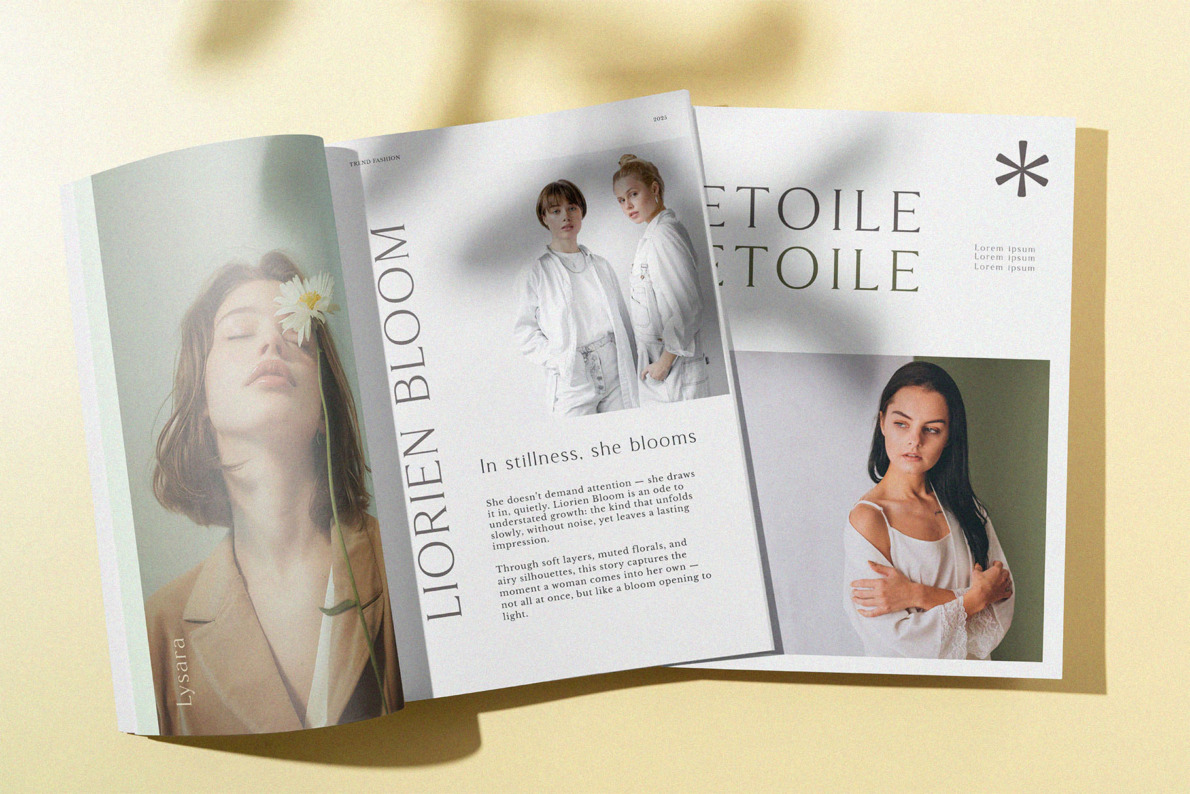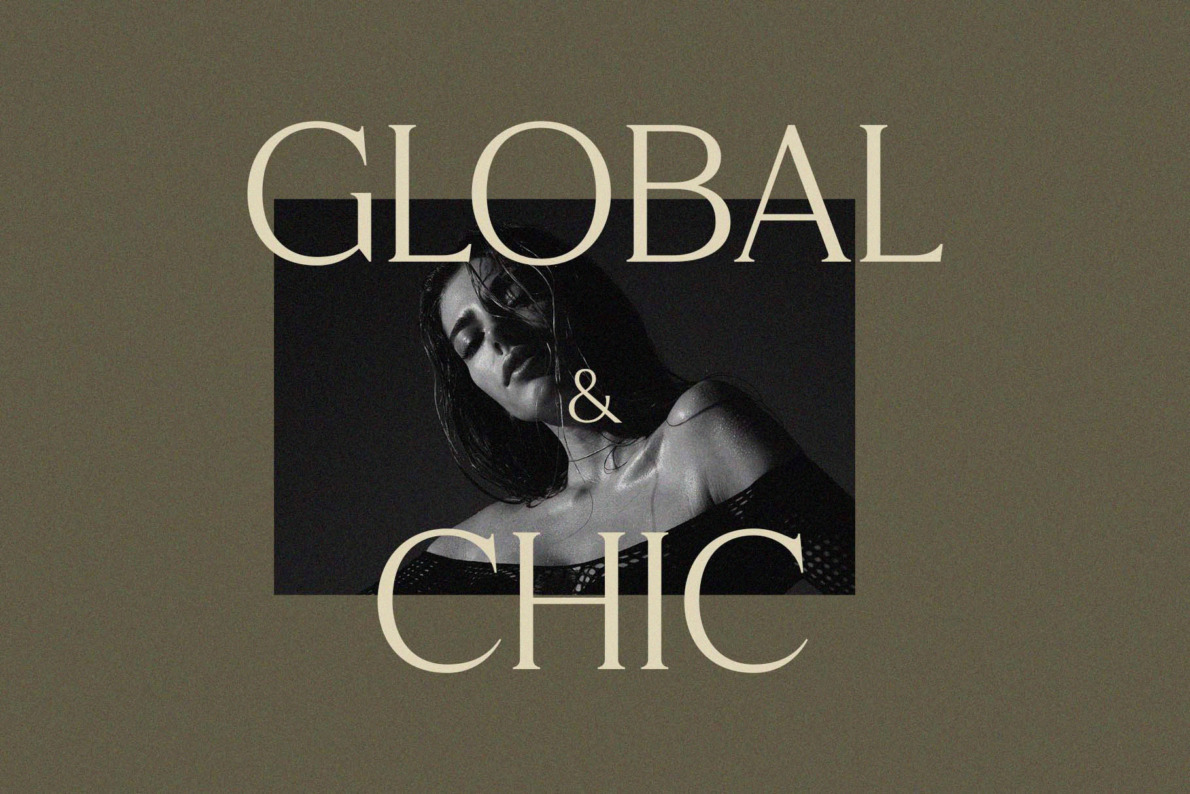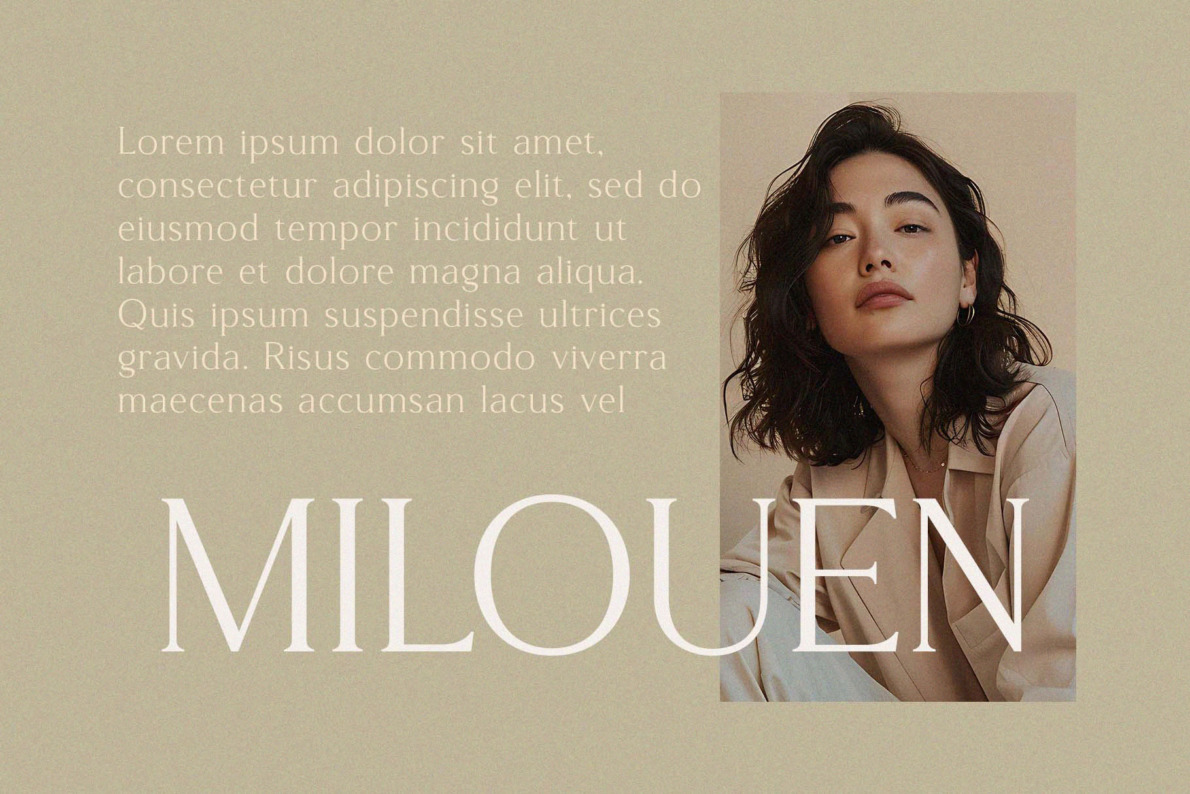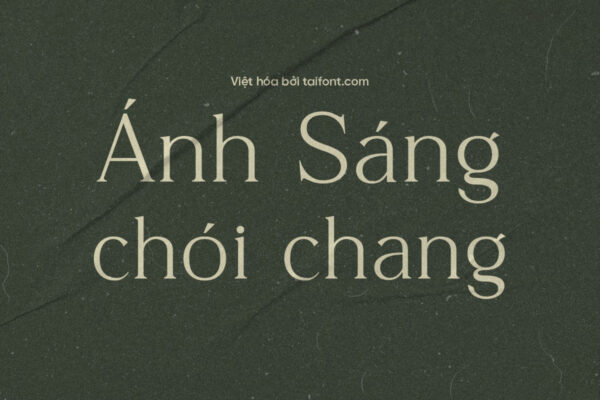
Giới thiệu về Font TF Galbety Việt hóa
TF Galbety Việt hóa là một font chữ có chân (serif) mang vẻ đẹp tinh tế, hiện đại và đầy cuốn hút. Với những đường nét được thiết kế tỉ mỉ, sắc sảo nhưng vẫn giữ được sự mềm mại, Galbety toát lên phong thái sang trọng và đẳng cấp, rất phù hợp cho những thiết kế cao cấp và đầy tính nghệ thuật.
Font này là lựa chọn lý tưởng để tạo nên sự ấn tượng và chuyên nghiệp, đặc biệt là trong các lĩnh vực yêu cầu tính thẩm mỹ cao:
- Thiết kế thời trang: Hoàn hảo cho các thương hiệu thời trang cao cấp, từ nhãn mác sản phẩm, lookbook, đến các chiến dịch quảng bá bộ sưu tập. Galbety giúp truyền tải sự tinh tế, phong cách và đẳng cấp của trang phục, nâng tầm giá trị thương hiệu.
- Thiết kế tạp chí: Lý tưởng cho các tạp chí về thời trang, làm đẹp, lối sống, nghệ thuật hoặc các ấn phẩm cao cấp khác. Font này giúp các tiêu đề, bài viết, hoặc các phần nội dung trở nên cuốn hút, chuyên nghiệp và dễ đọc, nâng tầm đẳng cấp của tạp chí.
Với TF Galbety Việt hóa, bạn có thể dễ dàng thổi hồn tinh tế và sự sang trọng vào các thiết kế, tạo ra những sản phẩm không chỉ đẹp mắt mà còn đầy cảm xúc và sức hút.